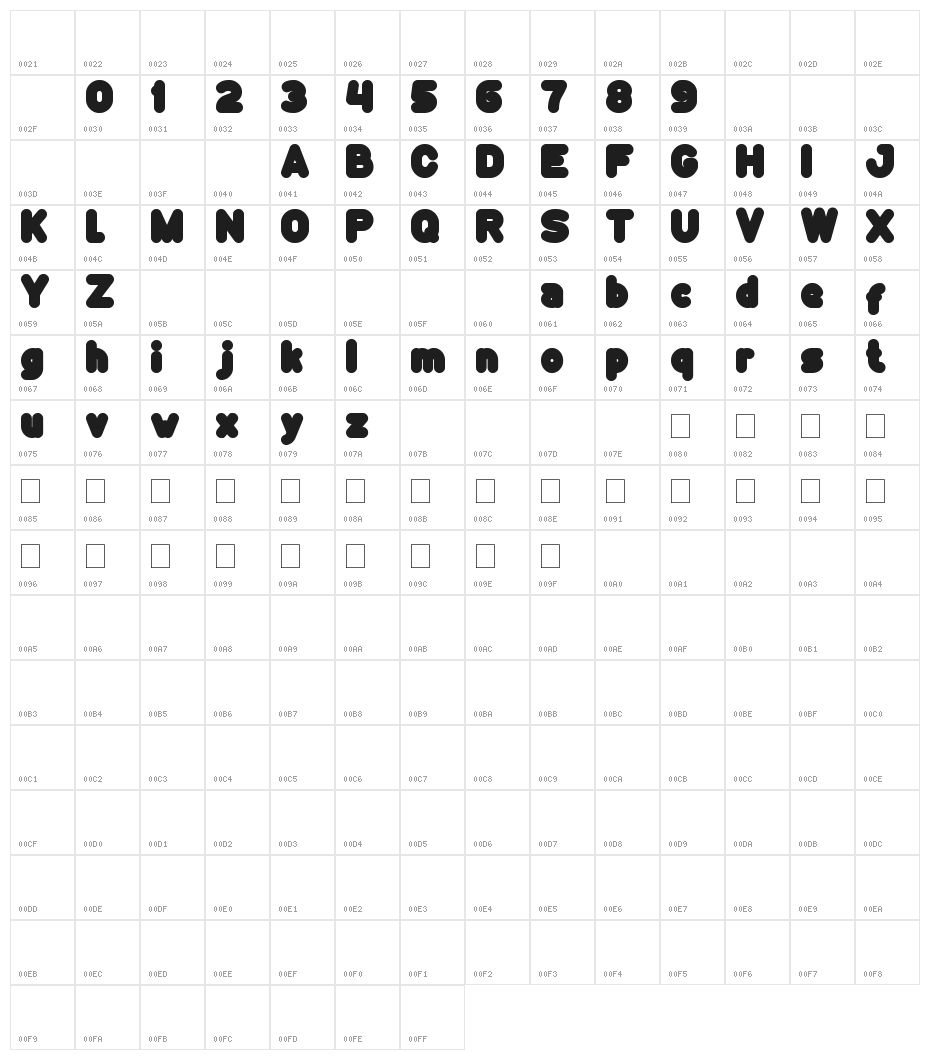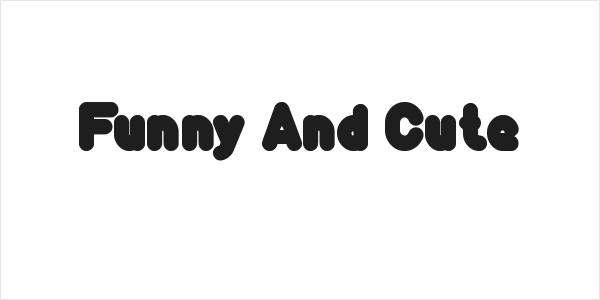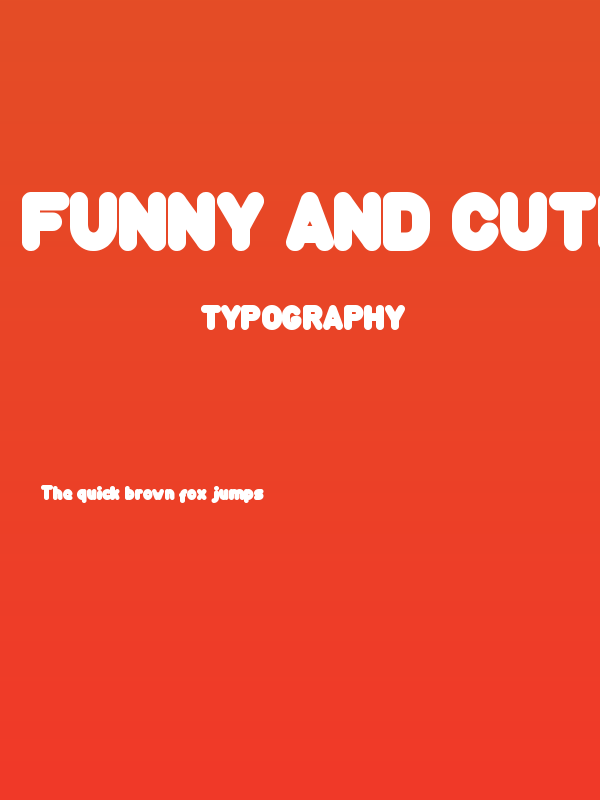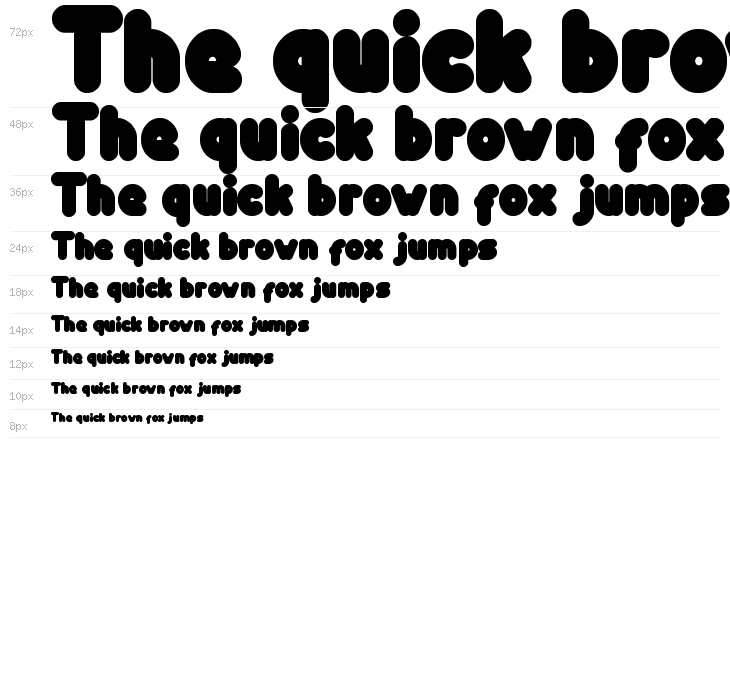
Funny And Cute Font
| النمط العام | Playful, Fun |
| مشاريع مقترحة | Ideal for children's books, playful branding, party invitations, and fun social media graphics. |